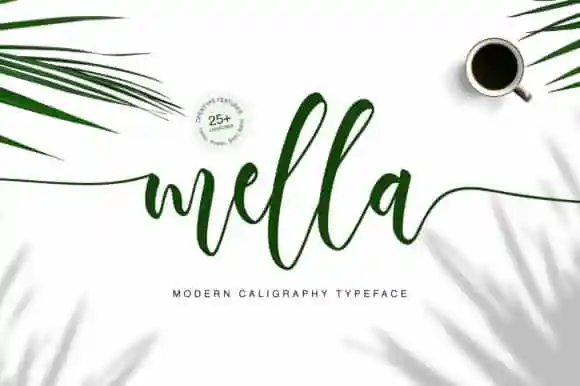
Mella Calligraphy Font – Download Grátis
A Mella Calligraphy Font é uma elegante tipografia à base de caligrafia com diversas alternativas estilísticas que destaca-se por seu aspecto natural e luxuoso, perfeitamente adaptado para projetos únicos e extraordinários. Esta fonte traduz a sofisticação da caligrafia em um formato digital, mantendo um tom amistoso sem comprometer a elegância e profundidade de sua forma. A Mella é ideal para criações originais e de alto nível, seja para cartões de convite, embalagens de produtos, citações, design de produto, arte manual, rótulos, fotografia ou marca. Com seu estilo clássico, essa fonte se adapta perfeitamente a uma variedade de aplicações digitais e impressivas. Seja para um projeto simples ou complexo, a Mella é sempre o elemento criativo necessário para dar vida à sua ideia. Experimente-a agora e transforme suas criações em verdadeiros espetáculos visuais.